実用手描文字 『実用図案文字と意匠』新装改訂復刻版
2017年8月30日から青幻舎より大正、昭和の描き文字図案集復刻シリーズ第2弾として「実用手描文字 『実用図案文字と意匠』新装改訂復刻版」が発売された。
本書は『実用図案文字と意匠』(大正15年刊、姉崎正広編)の実用図案文字を完全収録し再構成した内容で、20世紀初頭の商業美術というカテゴリーで活躍した図案家たちは様々な媒体(ビラ・チラシ、看板、ポスターなどに)に合わせて、ひと文字、ひと文字、制作された「描き文字」500点以上を収録している。
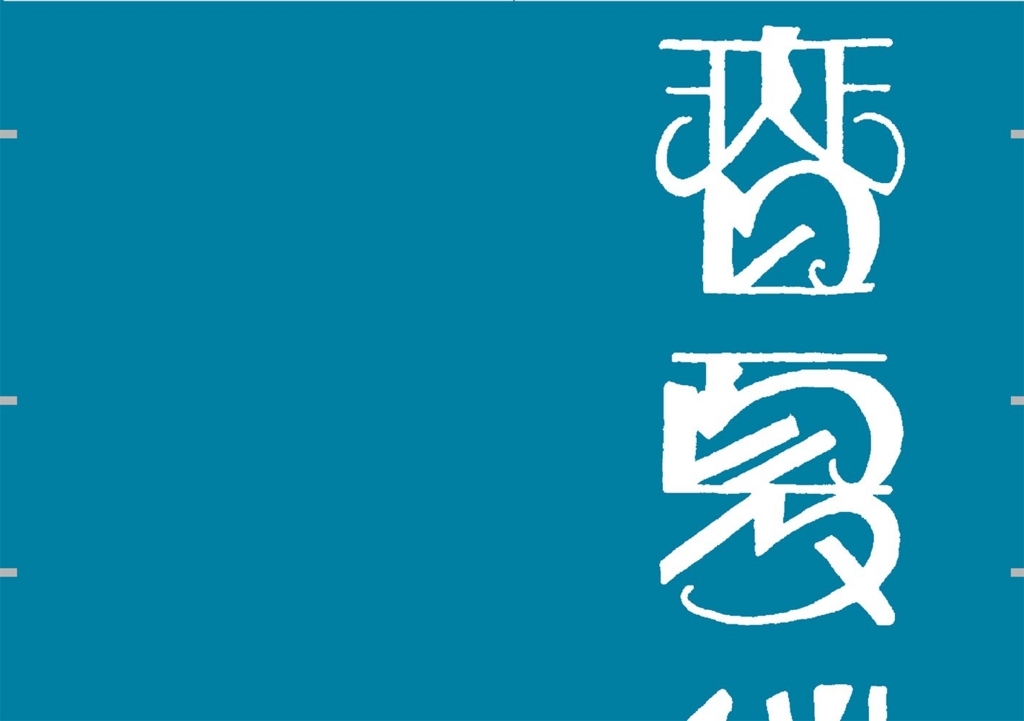
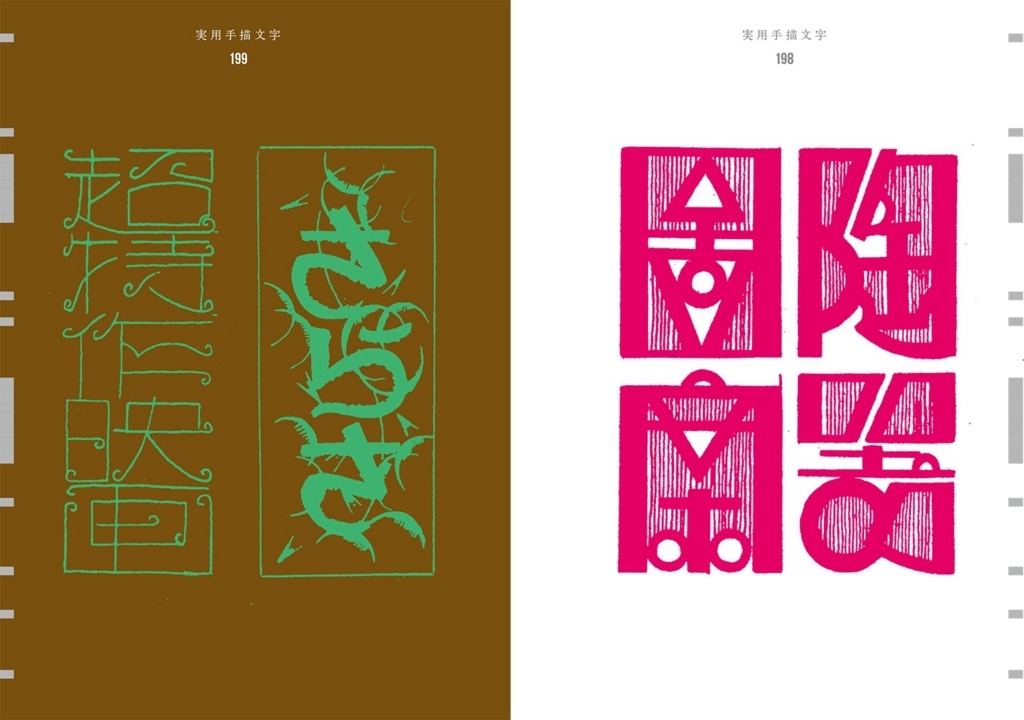
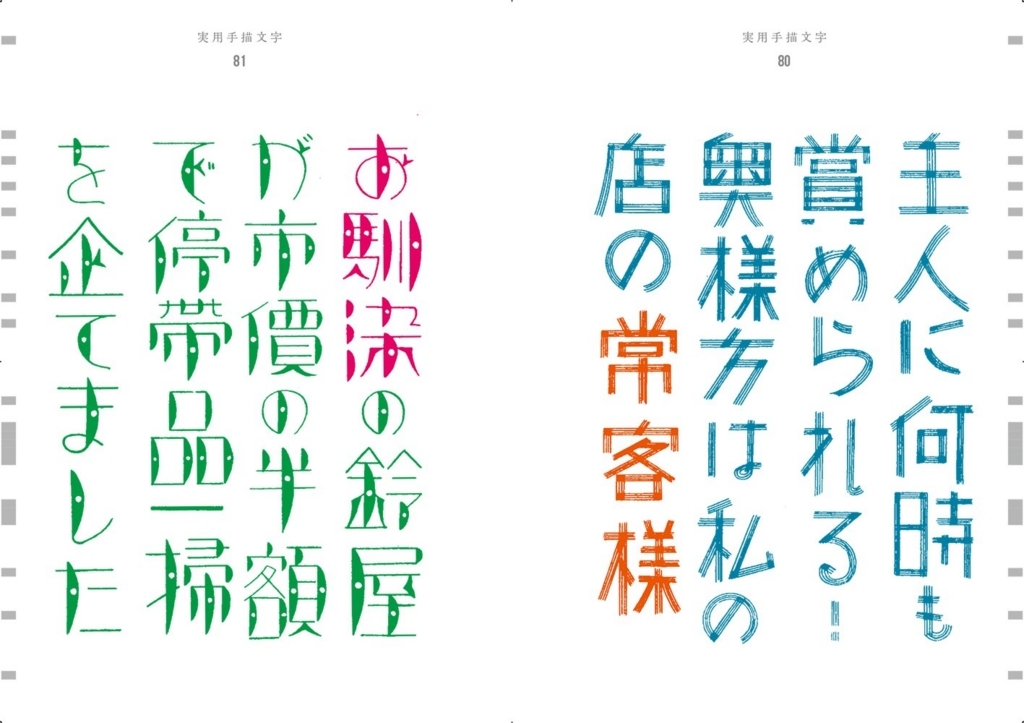
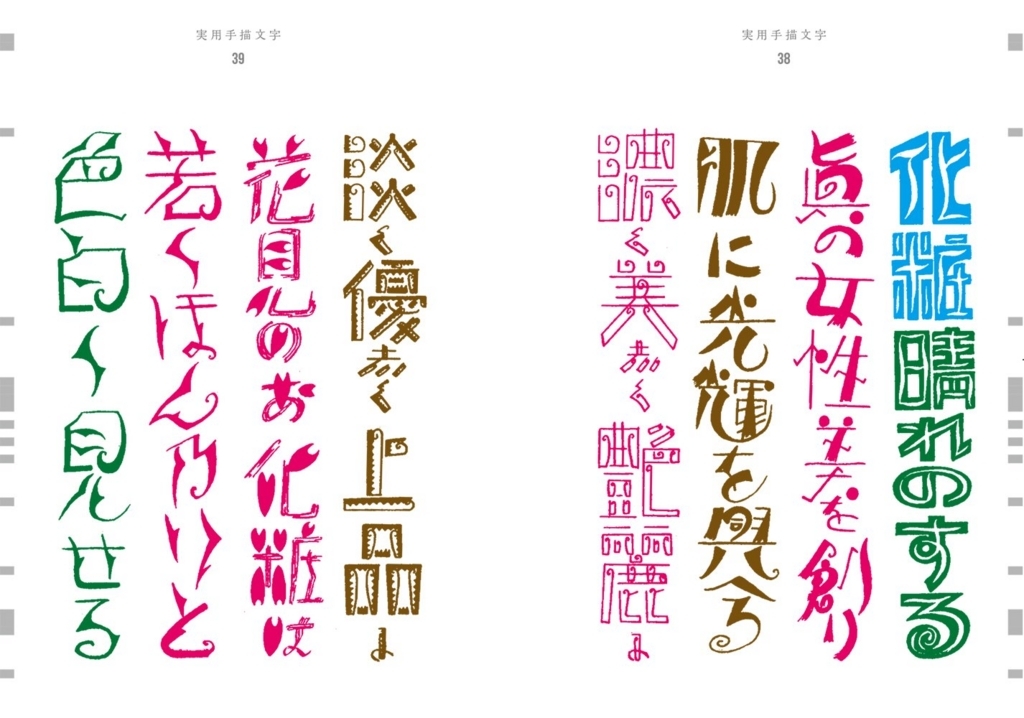
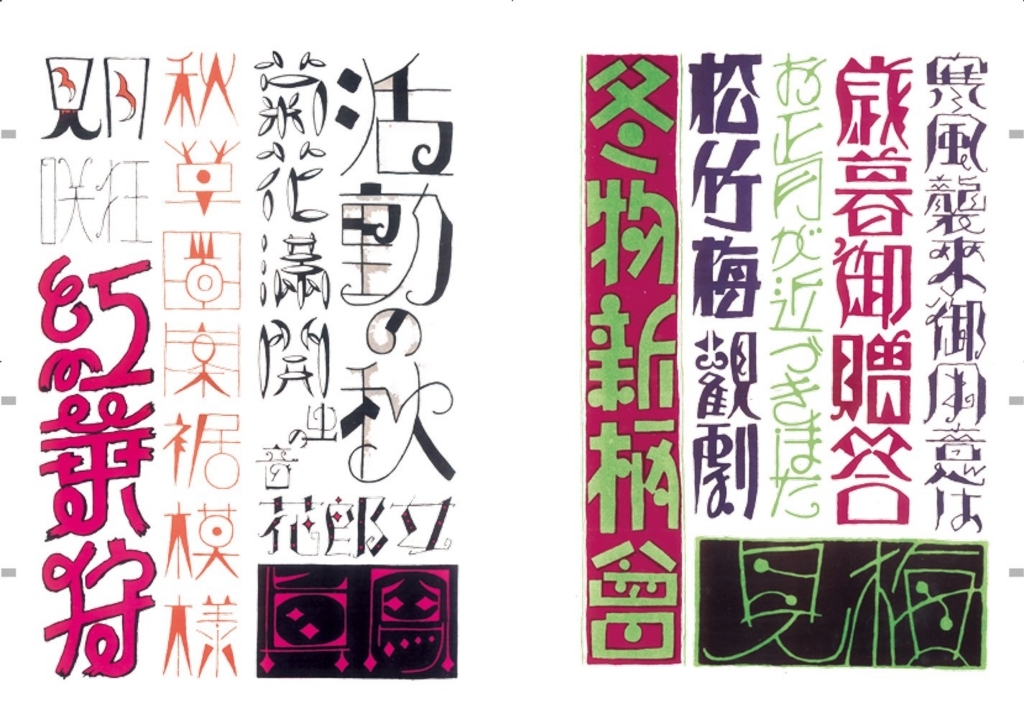
現代の人間の目からは文字であり、アートな感じも強い。